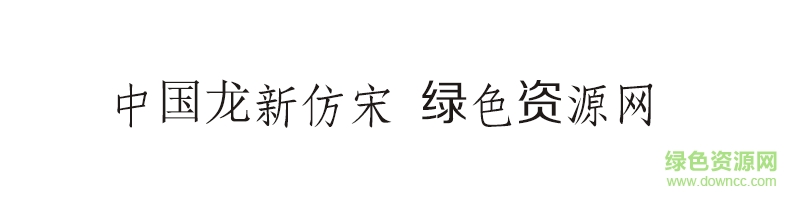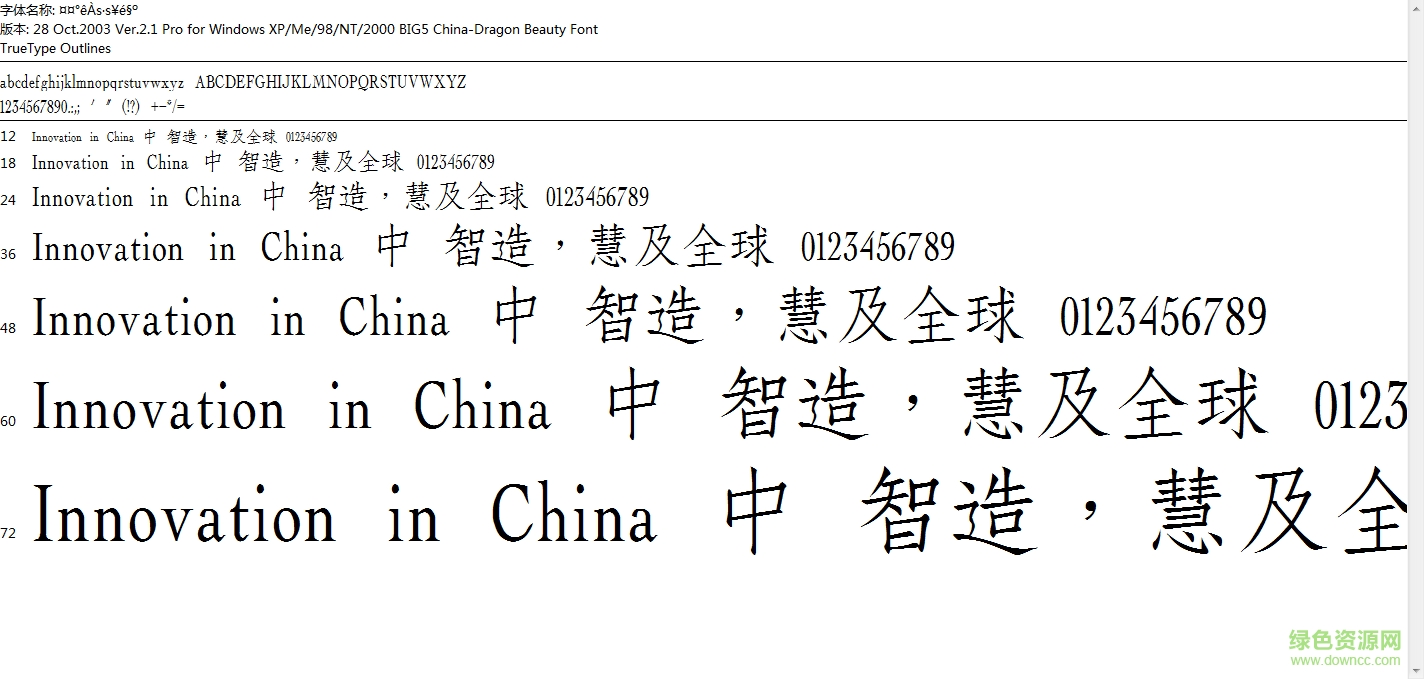
中國龍新仿宋字體是一款偏細字體,字型簡約大氣,非常正統(tǒng),給人一種很正式的感覺,應用范圍非常廣泛,如廣告設計、包裝印刷、平面設計等領(lǐng)域,喜歡的朋友歡迎來綠色資源網(wǎng)下載!
中國龍新仿宋是非常常用的中文字體,保留仿宋字體的經(jīng)典形態(tài)結(jié)構(gòu),樣式簡單、美觀,此款字體的缺點是不是每款字體都可以正常顯示。